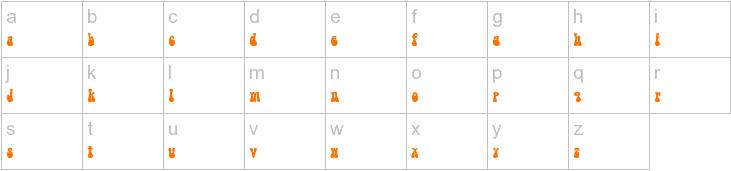
Indisch, Bollywood
suche eine Schrift die sehr emotionl, indisch und in Richtung Bollywood geht.
Mache gerade ein Kommunikations-Design fürs Studium, habe zwar schon ein paar Schriften gefunden, aber so richtig glücklich bin ich noch nicht.
Es geht hier um ein fiktives indisches Restauraunt, bei dem typisch indisch, also mit den Fingern, gegessen wird. Es soll alles sehr Emotional und nach Freude aussehen.
Sieht irgendwie undrund aus. Warum nicht lieber sowas?
[specimen=Mughal-e-Azam:1y5o27xq]24707[/specimen:1y5o27xq]
[specimen=Dilwale Dulhania Le:1y5o27xq]24395[/specimen:1y5o27xq]
... oder ganz »eindeutig«:
[specimen=Hum Aapke Hain Koun:1y5o27xq]16208[/specimen:1y5o27xq]
Ja schade, aber die letzte schrift gefällt mir auch schon ma, habe nun noch diese Schrift gefunden, werde nochmal in ruhe abwegen welche ich nehme, was halt ihr den von dieser:
was halt ihr den von dieser …
Würde ich spontan nicht unbedingt mit dem Thema in Verbindung bringen.
Ja schade, aber die letzte schrift gefällt mir auch schon ma, habe nun noch diese Schrift gefunden, werde nochmal in ruhe abwegen welche ich nehme, was halt ihr den von dieser:
Finde ich unter den genannten Suchkritrien abwegig.